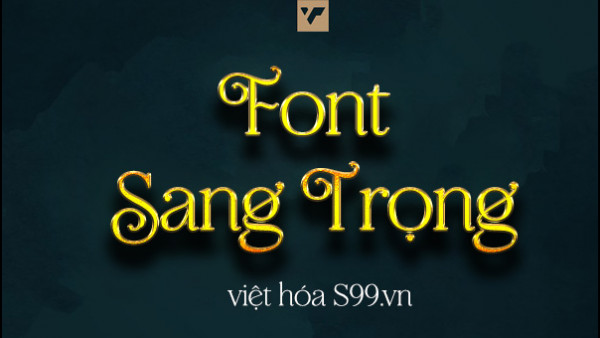
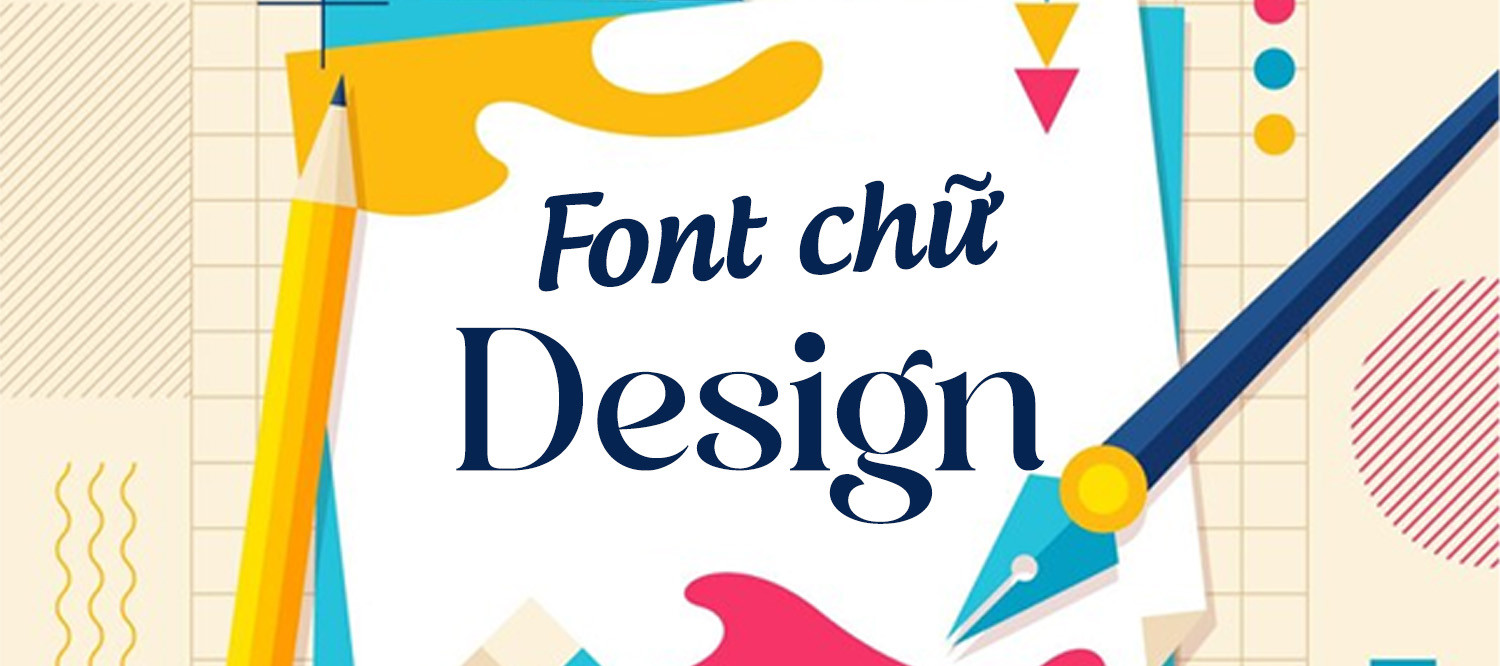
Thiết kế đồ họa không chỉ là việc sắp xếp các hình ảnh và màu sắc mà còn là việc lựa chọn font chữ phù hợp để truyền tải thông điệp một cách hiệu quả. Font chữ đóng vai trò quan trọng trong việc tạo dựng phong cách và cá tính cho bất kỳ dự án thiết kế nào. Dưới đây là một số danh mục font chữ design phổ biến mà bạn có thể tham khảo và sử dụng cho các dự án của mình.
Font chữ ký (signature fonts) thường được thiết kế để phản ánh đặc trưng cá nhân hoặc thương hiệu. Font này thường có các đường nét mềm mại, tạo cảm giác nhẹ nhàng và thanh thoát. Điều này giúp nó thích hợp để tái hiện chữ ký thực tế một cách chân thực nhất. Mặc dù đôi khi có thể có những chi tiết nghệ thuật nhất định, nhưng hầu hết font chữ ký được thiết kế với phong cách hiện đại và đơn giản để phù hợp với các mục đích sử dụng trong thiết kế hiện đại. Một số font chữ ký phổ biến của nhà S99.vn để bạn có thể tham khảo bao gồm:
Font chữ ký TH Corinthiago Việt hóa
Font chữ viết tay, chữ ký mềm mại TH Jalliya
Font chữ viết tay SVN-Flamingo Script ấn tượng
Font chữ ký viết tay mềm mại SVN-Janelotus
Font chữ nghiêng, viết tay SVN-Darleston Việt hóa
Font chữ viết tay, chữ ký TH Fineshly
Font chữ viết tay ấn tượng SVN-Alogittyon
Font chữ viết tay, chữ ký mềm mại TH Signatura
Font chữ viết tay cho thiệp cưới, đám cưới TH Chemistry
Font chữ viết tay lãng mạn, độc đáo TH Blackstand
Font thư pháp là những font mang đậm nét nghệ thuật và truyền thống văn hóa. Thường được thiết kế dựa trên các phong cách chữ viết cổ điển từ các nền văn hóa khác nhau như chữ Hán, La Mã, hay chữ cái châu Âu cổ điển. Đặc điểm của font thư pháp là đường nét uốn lượn, sự tỉ mỉ trong từng nét vẽ, tạo nên sự tinh tế và sang trọng. Font thư pháp thường được sử dụng trong các thiệp cưới, bài thơ và các tác phẩm nghệ thuật khác. Dưới đây là top 4 font chữ thư pháp phổ biến của nhà S99.vn để bạn có thể tham khảo sử dụng cho thiết kế của mình:
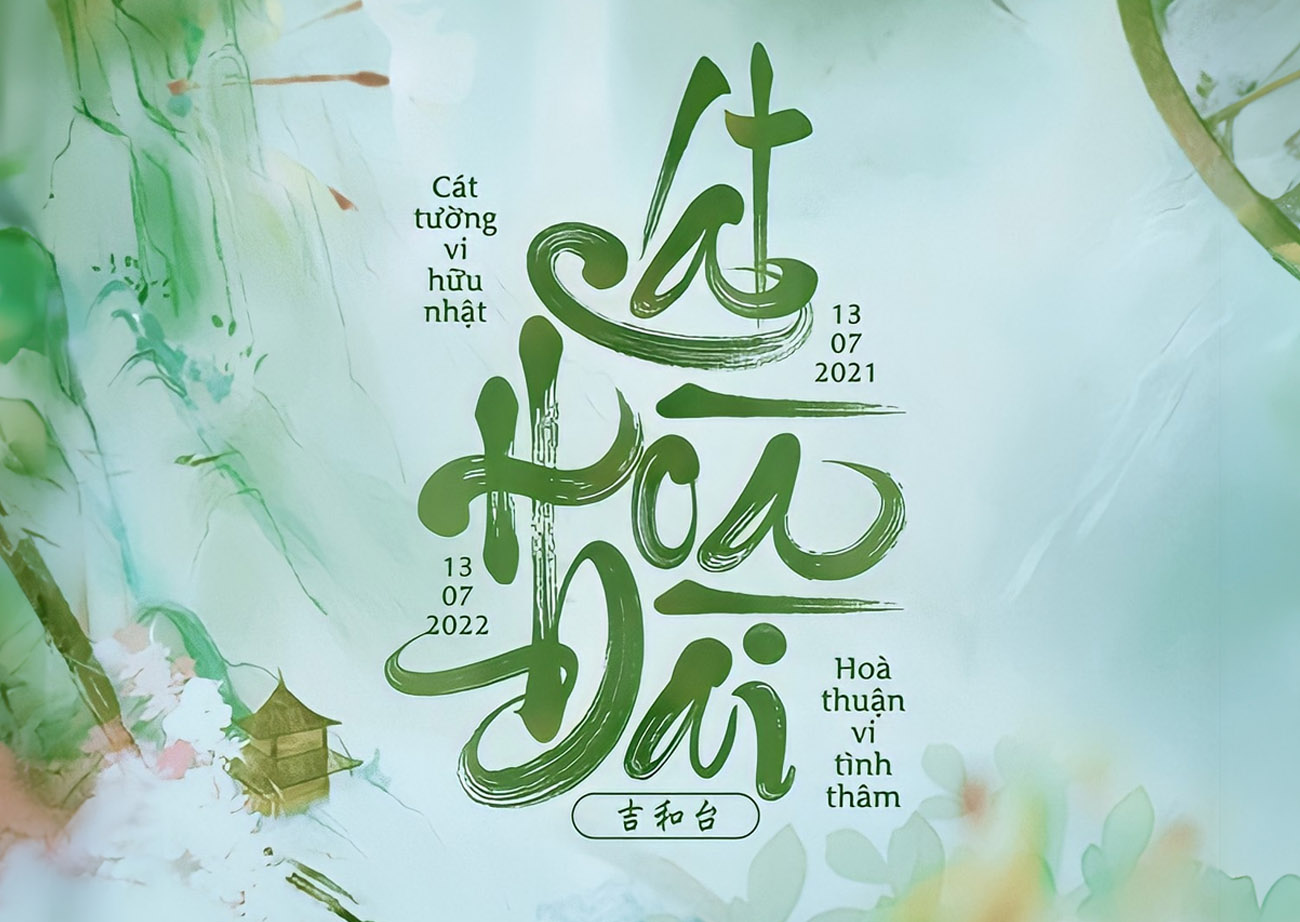
Font chữ thư pháp Đức Thủy: Đây là một trong những loại font chữ mang đậm nét trang nhã và tinh tế của nghệ thuật thư pháp truyền thống. Với đường nét uốn lượn mềm mại, Thư Pháp Đức Thủy thường được sử dụng để tạo điểm nhấn sang trọng và đặc biệt trong thiết kế văn bản, thư pháp sống động, và tranh treo tường.
Font chữ thư pháp Đại Tự: Với từng nét bút cong và đường viết uốn lượn mềm mại, Đại Tự thể hiện sự tinh tế và sự uyển chuyển của nghệ thuật viết thư pháp. Đặc biệt, những nét chữ được uốn lượn tỉ mỉ, từng chi tiết nhỏ như đường viền và độ dày của nét bút đều thể hiện sự tinh tế và chuyên nghiệp trong thiết kế.
Font chữ thư pháp FZ Tiểu Tự Việt hóa là một trong những lựa chọn đáng chú ý cho các dự án thiết kế văn hóa, đặc biệt là trong việc thể hiện nét đẹp truyền thống. FZ Tiểu Tự mang đến một sự đa dạng về các ký tự và mẫu chữ cái, từ những chữ nghiêng mềm mại đến những nét cứng cáp và mạnh mẽ, cho phép người sử dụng linh hoạt thay đổi phong cách phù hợp với mỗi bài thiết kế.
Font chữ TH Hidayatullah: Với thiết kế lấy cảm hứng từ nghệ thuật thư pháp, font này mang đậm phong cách truyền thống nhưng vẫn không kém phần hiện đại. Những nét chữ cong và uyển chuyển của Hidayatullah tạo nên một sự hài hòa đặc biệt, thu hút mọi ánh nhìn và thích hợp cho các thiết kế đồ họa, poster nghệ thuật,...
Font font chữ design hoạt hình là những font có hình ảnh ngộ nghĩnh, lạ mắt và thường được sử dụng trong thiết kế đồ họa, đặc biệt là cho trẻ em và các sản phẩm giải trí. Các font hoạt hình thường có nét chữ to, đặc điểm rõ nét, màu sắc tươi sáng và biểu cảm mạnh mẽ, giúp tăng tính thú vị và truyền tải thông điệp một cách dễ dàng. Một số font hoạt hình phổ biến của nhà S99.vn có thể kể đến như:
Font chữ hoạt hình trẻ em vui nhộn SVN-Carista
Font chữ hoạt hình dễ thương, cute SVN-Carrotflower
Font chữ hoạt hình hơi hướng kinh dị SVN-Endless Sorrow
Font chữ hoạt hình Việt hóa TH Gyoza đáng yêu
Font hoạt hình TH - Jelly Bomb Việt hóa vui nhộn
Font chữ hoạt hình, trẻ em, cute SVN-Sablon Washed Super
Font chữ viết tay cute, dễ thương SVN-Nuit
Font chữ hoạt hình, mềm mại, dễ thương SVN-Moon Earth
Font dễ thương, vui vẻ, cute, vui nhộn SVN-Marujo
Font chữ viết tay hoạt hình, trẻ em SVN-Progs
Font thể thao thường có sự mạnh mẽ, năng động và thể hiện tinh thần đồng đội, sự cạnh tranh và sức mạnh. Các font này thường có đường nét mạnh mẽ, góc cạnh và thường được sử dụng trong thiết kế quảng cáo, biển báo thể thao, hay các sản phẩm liên quan đến hoạt động thể thao và thể dục. Top các font chữ design thể thao nổi bật của S99.vn có thể kể đến là:
Font chữ thể thao cứng cáp TH The Bracet Việt hóa
Font chữ thể thao mạnh mẽ và cứng cáp TH Slecfie Việt hóa
Font chữ thể thao phong cách sans serif TH Lebrone-Bold Việt hóa
Như vậy, việc lựa chọn font chữ phù hợp không chỉ đơn giản là việc chọn lựa hình thức mà còn là việc truyền tải thông điệp và phong cách cho sản phẩm thiết kế. Bằng việc hiểu rõ từng danh mục font chữ design và cách áp dụng chúng, bạn sẽ có thêm sự lựa chọn và sáng tạo trong công việc thiết kế của mình. Hy vọng bài viết này đã cung cấp cho bạn những thông tin hữu ích về các loại font chữ phổ biến trong thiết kế đồ họa hiện nay.